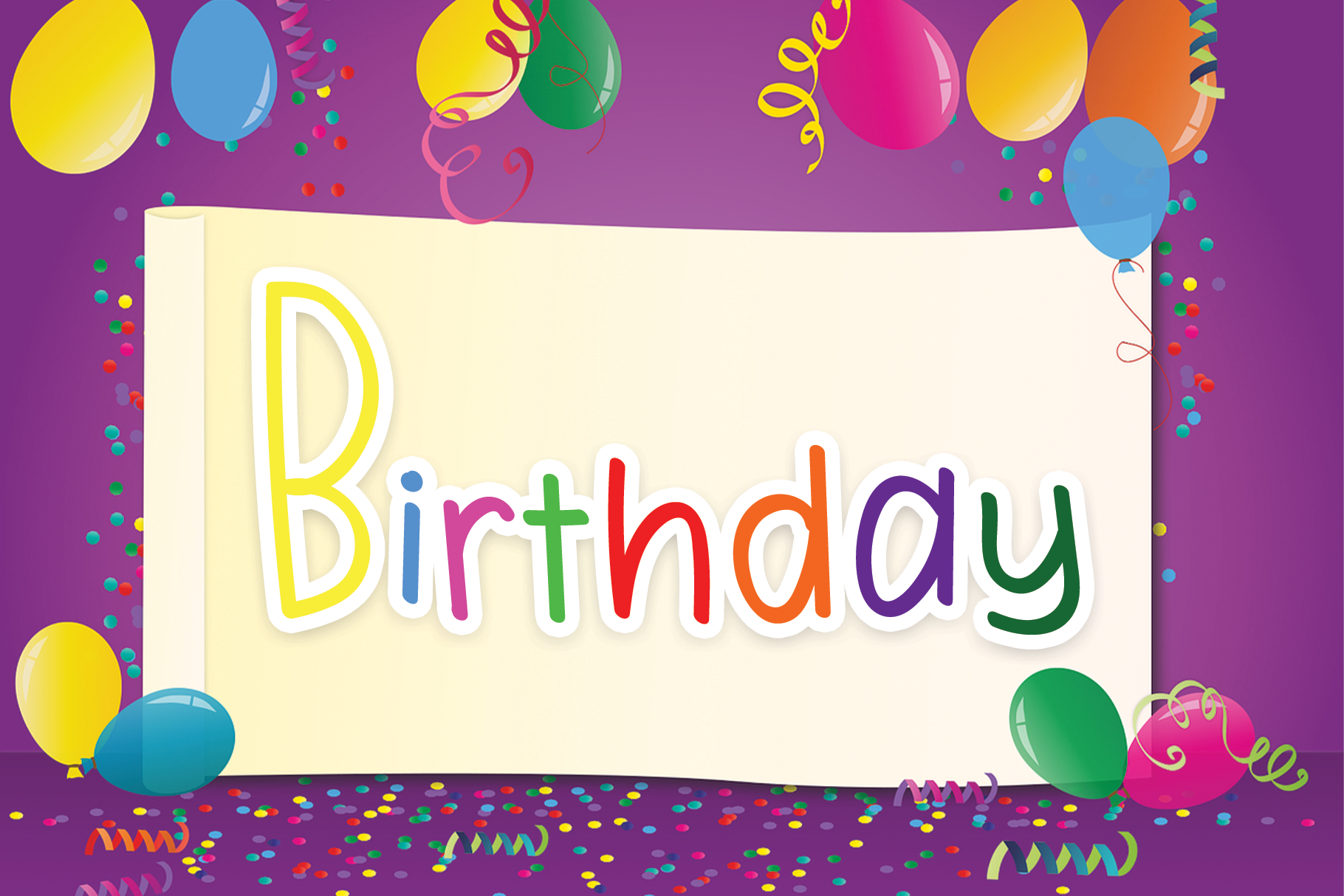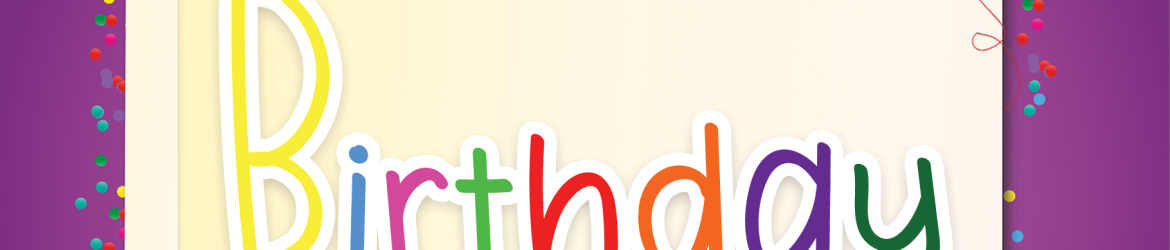
Birthday Font – Download Grátis
Esta fonte é perfeitamente desenhada para criar designs alegres e naturais, especialmente adequada para temas infantis. Com seu script simples e natural, ela se destaca em estilos casualmente desenfadados. Este tipo de fonte é ideal quando combinada com cores vivas, criando design gráficos atraentes para crianças que celebram aniversários ou tem assuntos relacionados. Ideal tanto para uso em materiais educacionais quanto em criações de scrapbooking e decoração infantil. Ela oferece um toque especial para qualquer projeto que você esteja planejando criar, tornando-o uma opção ótima para designers buscando uma fonte atemporal que se destaca na internet. A fonte ‘Birthday Font’ é perfeitamente adaptada ao designer el hotcig, capaz de transformar pequenos detalhes em design gráfico incrivelmente atraentes e únicos.